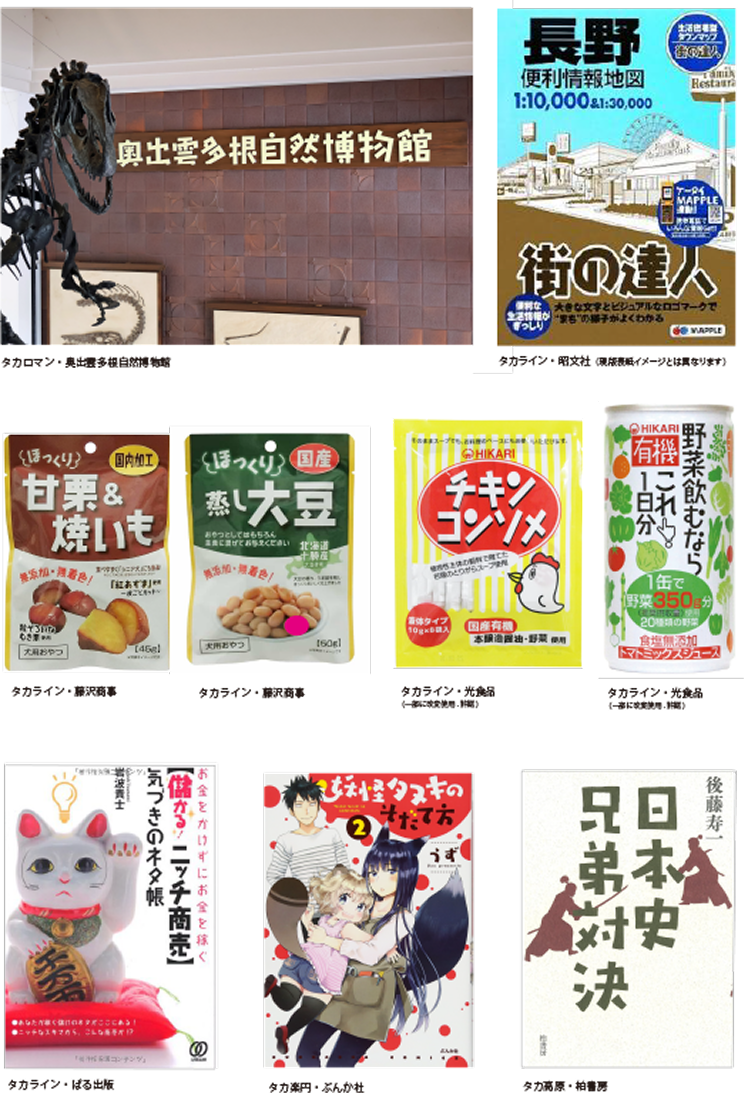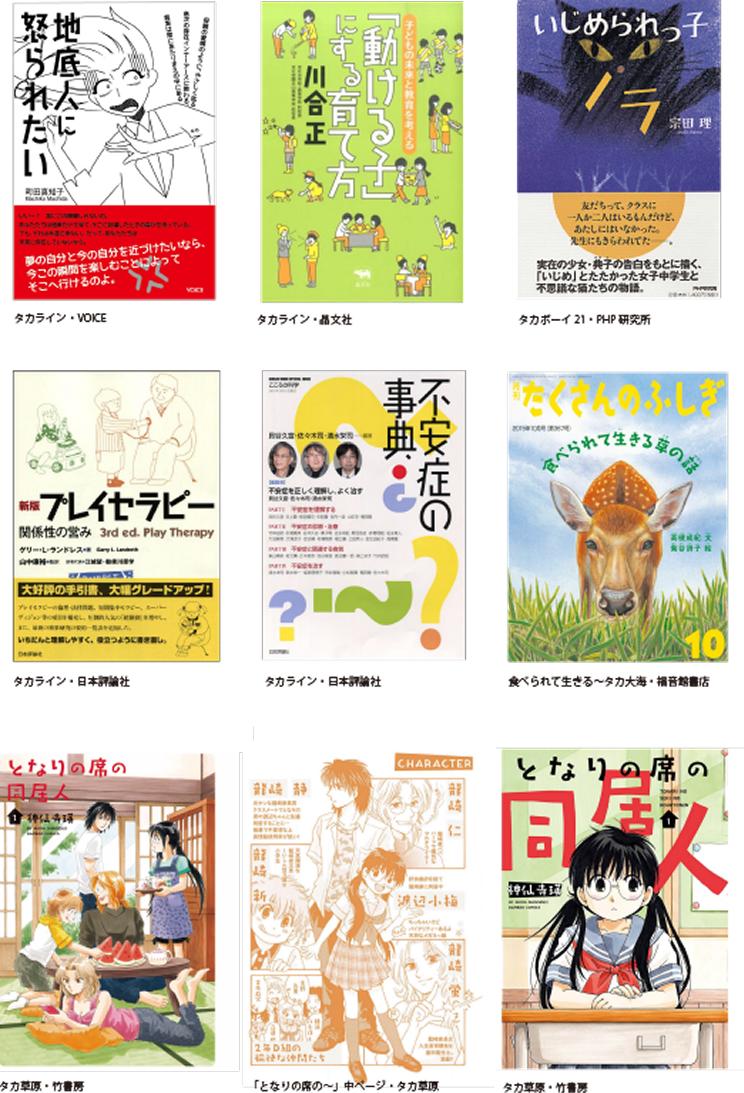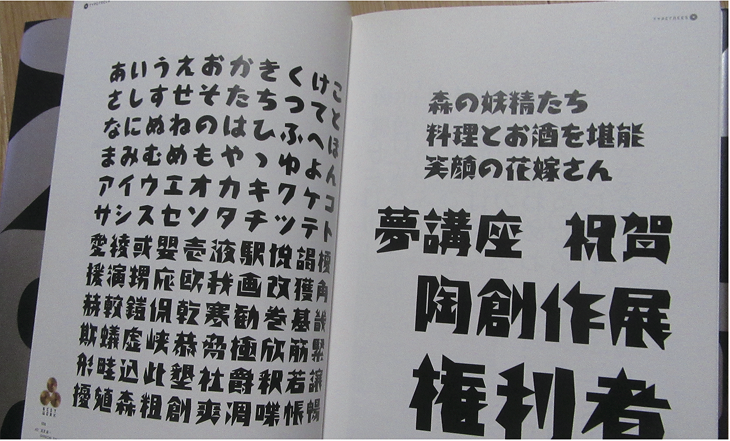
書体デザイナー高原新一氏の個性豊かな書体
タカ書体とは
タイプ作家の高原新一氏が創作する書体ブランドです。
その最大の特徴は、「手書き風の味わいと温もり」をテーマにした個性豊かなデザイン。
どの書体も人間味に溢れ、温もりある魅力の顔をもってます。
タカ書体の特徴
タカ書体は、手書きの暖かみと人間味あふれるデザインが魅力で、見る人に親しみやすい印象を与えます。ファミリーを基本として制作し、タカ書体の原点でもあるアナログ感覚の「手書き書体」も数多く取り揃えております。
一貫した創作テーマは「手書き風の味わいと温もり」です。
・手書き感のあるデザイン
機械的な均一性をあえて避け、文字のバランスや線の表情を意図的に崩すことで、手書きのような親しみやすさや躍動感を表現しています。
・デザイン性の高さ
ただ手書きを模倣するだけでなく、一つひとつの文字にアクセントやリズムを持たせることで、高いデザイン性を実現しています。その作品は、日本タイポグラフィ年鑑のグランプリ受賞など、数々の実績を持っています。
・多様なラインナップ
代表作である「タカハンド」をはじめ、丸や三角のエレメントを取り入れた「タカリズム」、直線的なフォルムが斬新な「タカライン」など、それぞれ異なるコンセプトを持った多彩な書体を展開しています。
主な用途
タカ書体のフォントは、そのユニークなデザインから、特に以下のような場面での利用に適しています。
・広告・POP
親しみやすく、目を引くデザインが、商品のキャッチコピーやイベントの告知などで大きな効果を発揮します。
・パッケージ:
温かみのあるデザインは、食品や雑貨などのパッケージに手作り感や安心感を与えるのに役立ちます。
・見出し・タイトル:
伸びやかで力強い書体は、タイトルや見出しとして使うことで、生き生きとした印象を与えられます。
書体の種類
タカ書体には、個性が際立つ多くのフォントがあります。
タカハンド:タカ書体の代表作。手書きの風合いを活かした、自由で伸びやかなデザインが特徴です。
タカリズム:丸や三角といったユニークなエレメントが取り入れられており、弾むような楽しさを表現できます。
タカライン:漢字はすべて直線処理が施されており、シャープでインパクトのある斬新な書体です。
タカ風太:伸びやかで元気なイメージの手書き書体です。パッケージやキャプションなど、キャッチーな表現に使われます。
高原新ー プロフィール
日本タイポグラフィ協会会員。
日本タイポグラフィ年鑑グランプリ受賞、ニューヨークTDC展入選、
CSデザイン賞・装飾部門銀賞、石井賞タイプフェイスコンテスト入賞、
国際タイプフェイスコンテスト入賞等、多くの受賞歴をもつ。
タイプデザイナー、タイポグラファーとしてTV等で紹介。
これまでロゴタイプ、シンボルマーク等、CI、VIを多く制作。
個展、グループ展開催。高原新ー「意明絵字(いめえじ)の世界」自費出版。
絵文字作品は中学、高校美術教科書に掲載。